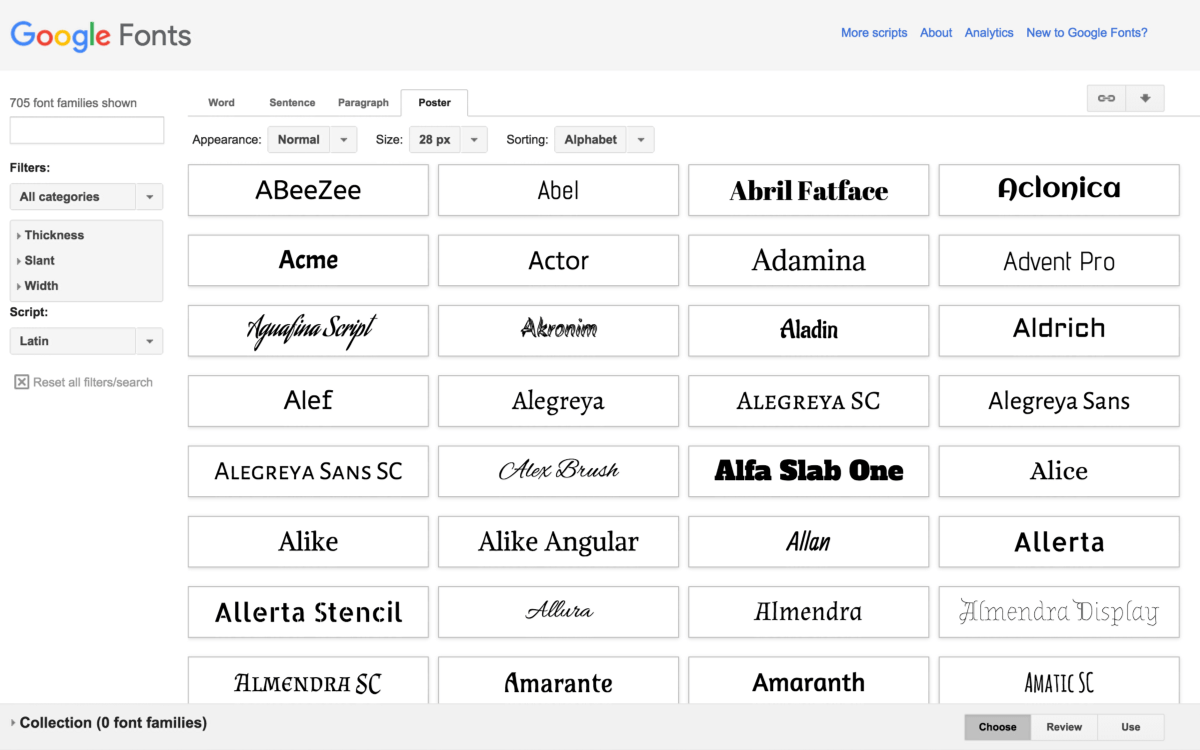
10 лучших шрифтов Google Fonts для заголовков сайта
Google Fonts — один из самых крупных архивов реально бесплатных шрифтов с сотнями гарнитур. Учитывая его универсальный характер и всеобщую доступность, теряется практически любой смысл использования обычных шрифтов по умолчанию. С помощью сервиса вы сможете реализовать разные нестандартные примеры типографики.
В данной статье найдете подборку из 10-ти бесплатных шрифтов Google Fonts, которые идеально подойдут для оформления заголовков сайта. Они установлены во многих веб-проектах по всему миру. Материал является переводом этой заметки от Jake Rocheleau.
1. Montserrat
Начнем с Montserrat. Он неплохо работает в разных местах, но в заголовках — особенно хорош. Его часто используют для навигации: в заглавных или прописных буквах, с нестандартными разрядами и различными стилями плотности.
Благодаря большому количеству стилей, можно получить много различных видов одного семейства. Он должен понравится дизайнерам, хотя подойдет не всем проектам. Если ищите уникальные и красивые шрифты для заголовков сайта, обязательно попробуйте Montserrat.
2. Merriweather
Альтернативой плотным Google шрифтам с засечками является Merriweather, также подходящий для контента страницы. Его гарнитура хорошо смотрится в любом месте сайта, и привлекает внимание.
Если пробуете Merriweather в больших заголовках, воспользуйтесь полужирным или полужирным курсивным решениями. Они выглядят чисто, хотя иногда требуется слегка изменить интервал между буквами. В любом случае, данный стиль и плотность символов обеспечивают большую легкость чтения.
Можно использовать в паре с рубленым шрифтом — эти два вида оформления естественным образом отделяют заголовки от текста под ними.
3. Josefin Sans
Josefin Sans — современный и классический, одинаково хорошо воспринимается и как шрифт джазовых эстрад 1950-х годов, и как шрифт первой страницы The New Yorker.
Заметно закруглен, его тонкие буквы требуют мало места по горизонтали. Вы можете попробовать его в заглавных или прописных стилях, с различной разрядкой, создавая множество уникальных вариантов на основе одного семейства.
Некоторые сайты лучше смотрятся с тонкими шрифтами заголовков. И если вам нужен именно такой, рекомендуем Josefin Sans с его уникальным дизайном символов и разнообразием стилей.
4. Arvo
Еще один Google шрифт с засечками, который многим нравится, — Arvo. Он очень заметен при использовании в полужирном виде. Лучше всего Arvo работает в блогах и онлайн-журналах, так как за него цепляется взгляд.
Это один из самых сильных web шрифтов Google в данном списке, а его дизайн с засечками привлекает максимум внимания.
Альтернативой может стать менее плотный Crete Round, но он не так эффективен, как Arvo.
5. Raleway
Raleway встречается на сайтах довольно часто. Выделяется своим оригинальным стилем и большим разнообразием вариаций.
Для большого текста с заголовками лучше всего будет работать средняя плотность шрифта, чтобы не слишком увеличивать интервал между буквами. Отступы по умолчанию обеспечивают четкое восприятие каждого слова.
6. Catamaran
Одним из новых Google шрифтов для сайта является Catamaran. Он предлагается с 9 значениями плотности — от тонкого до черного. Каждая символ имеет уникальный стиль, и это видно в более плотных вариантах. Используемые в заголовках, буквы реально сияют и выпрыгивают из страницы, напоминают материалы из подборки bold шрифтов.
Поскольку полужирные вариации очень темные, применять Catamaran нужно только в заголовках с большими размерами. Он неплохо выглядит практически в любом случае, но иногда создается ощущение слишком тяжелого и плотного шрифта.
7. PT Sans
PT Sans — мягкий, с закругленными краями и тонкими буквами. В заголовках предпочтителен полужирный стиль, поскольку иначе он кажется очень тонким. Для обычного текста такой вариант будет слишком мягким, но любые заголовки с ним смотрятся удивительно четко и читабельно.
Кстати, у него имеется парный шрифт PT Serif, который тоже выглядит неплохо. Хотя из этих двух решений большинство выбирает именно PT Sans. У него более гладкие кромки, чем у варианта с засечками, и для многих он кажется лучшим, особенно в блогах.
8. Open Sans
Open Sans — небольшой, гибкий и очень чистый. Заслужил место в данной коллекции благодаря своей простоте и тому, что он является одним из наиболее быстро загружаемых во всей библиотеке бесплатных шрифтов Google Fonts.
В целом большинство рубленых шрифтов хорошо работает на любых веб-проектах. Кроме того, вы можете использовать их как в заголовках, так и в основном тексте, что делает Open Sans разумным выбором для всего сайта.
Альтернативой служит Muli, обладающий множеством положительных характеристик жирного шрифта для заголовков, но у него большой размер загружаемого файла.